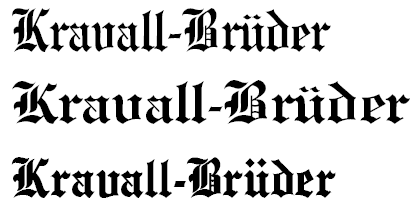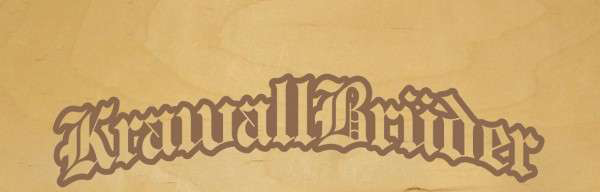
Suche Font. Bitte um Hilfe
ich suche diesen font aber find ihn nirgens und der namer fällt mir auch nicht mehr ein.........wäre nett wenn mir da jeamand weiterhelfen könnte..danke
Zwar tippe ich auch auf eine von den Lindenthal-Schriften aber eher auf die EnglischGravur (oben Normal, mitte Fett). Ähnlich auch die EnglishTowne (unten) von Dieter Steffmann, bei dieser ist aber vorallem das „B“ etwas anders.
Nachtrag: Es gibt die Schrift auch kommerziell als Engravers Old English von verschiedenen Anbietern.